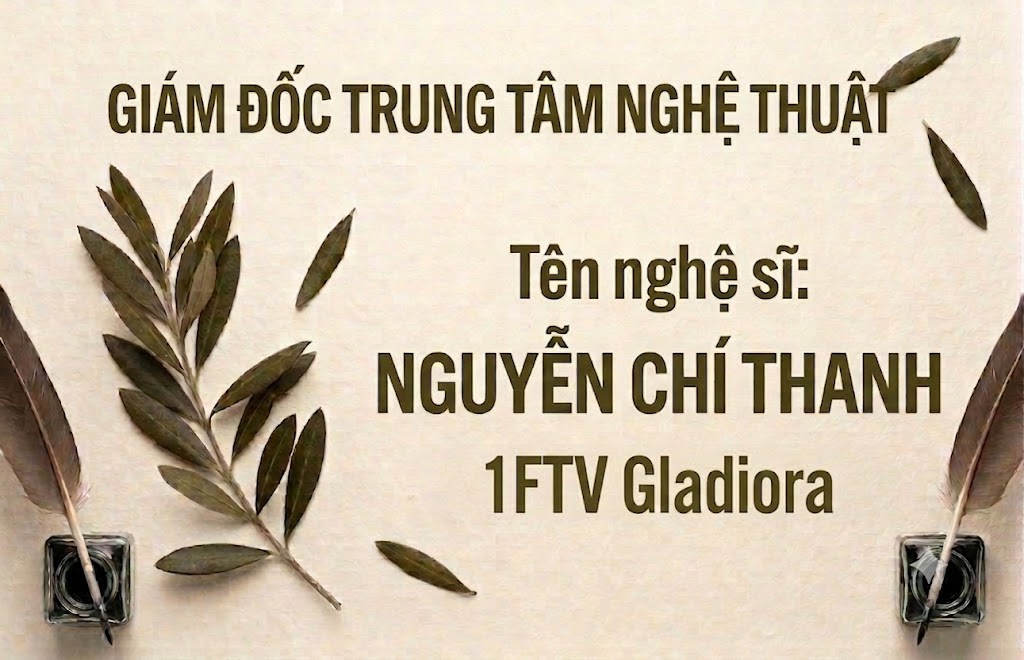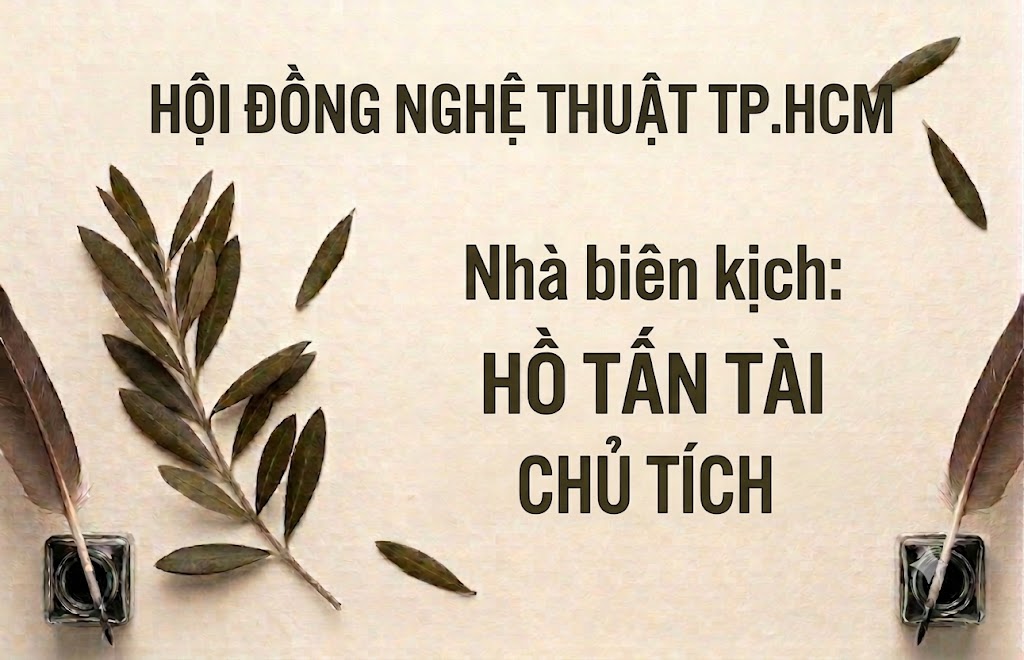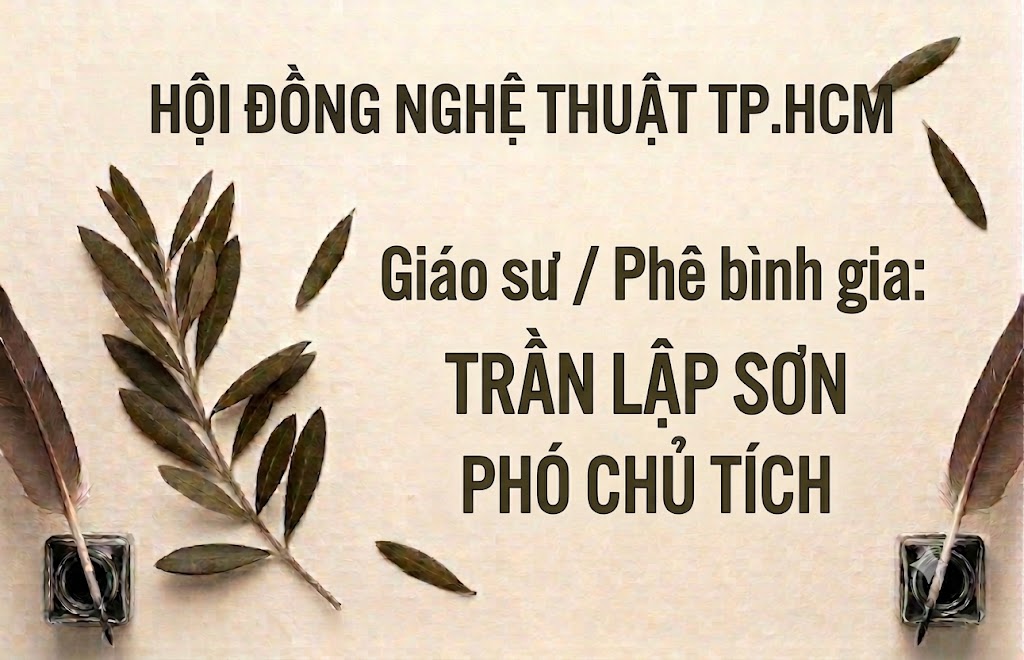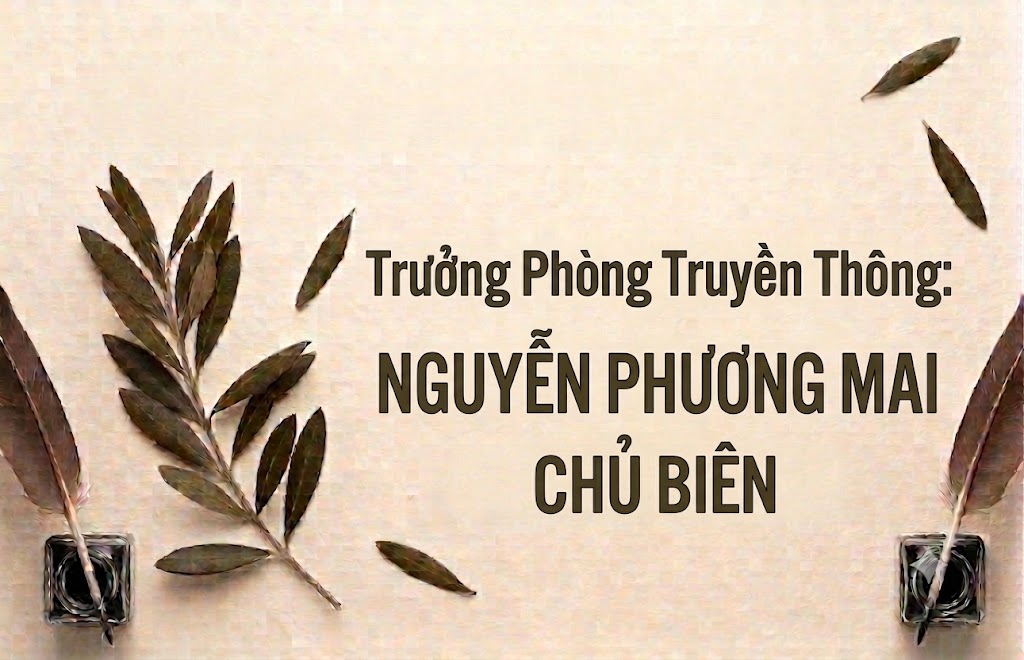
1FTV Gladiora
Trong xu hướng thiết kế tối giản hiện đại, các phông chữ không chân mang cấu trúc hình học tròn trịa luôn là lựa chọn hàng đầu của các designer.
Một kiểu chữ vừa thanh lịch, sạch sẽ lại vừa mang nét trẻ trung sẽ giúp các sản phẩm truyền thông của bạn dễ dàng tiếp cận và thu hút người xem hơn.
Nếu bạn đang tìm kiếm một bộ font nhẹ nhàng nhưng đầy tính nghệ thuật để làm tiêu đề video hay ảnh thu nhỏ, thì font 1FTV Gladiora chính là giải pháp lý tưởng.
Giới thiệu về font 1FTV Gladiora
Font 1FTV Gladiora là một bộ chữ thuộc thể loại display không chân mang phong cách geometric tối giản, thanh lịch và vô cùng hiện đại.
Bộ phông chữ này được tối ưu hóa hoàn chỉnh ở phiên bản 1.000, mang lại cấu trúc đường nét vô cùng mượt mà và nhất quán cho từng ký tự.
Sản phẩm xuất hiện trong bài viết sở hữu định dạng opentype layout cao cấp, đi kèm chứng thực kỹ thuật số và hệ thống nét chuẩn truetype outlines.
Nhờ các thông số kĩ thuật tối ưu này, phông chữ có khả năng hiển thị vô cùng sắc nét trên mọi nền tảng thiết kế đồ họa hiện đại mà không lo bị lỗi vỡ hình.
Đặc điểm nổi bật của phong cách thiết kế Gladiora
Sức hút lớn nhất của font 1FTV Gladiora đến từ phom dáng tròn trịa mang đậm tính chất hình học kết hợp cùng nét chữ thanh mảnh.
Các ký tự như o, e, c, a được tạo hình với những đường cong hoàn hảo, gợi lên sự thân thiện, nhẹ nhàng và đầy tinh tế cho toàn bộ văn bản.
Điểm cộng rất lớn của bộ font này là việc hỗ trợ trọn vẹn cả hệ thống chữ thường bên cạnh bộ chữ viết hoa cơ bản.
Điều này giúp bạn dễ dàng phối hợp hoa thường linh hoạt, khiến dòng tiêu đề trở nên tự nhiên, cuốn hút và thoáng mắt hơn khi hiển thị.
Khoảng hở giữa các nét chữ được tính toán khoa học, đảm bảo phần nội dung văn bản luôn rõ ràng và cực kỳ dễ đọc trên mọi thiết bị di động.
Để phông chữ vận hành mượt mà trên hệ thống máy tính, phiên bản font 1FTV Gladiora đã trải qua quy trình xử lý thông số kĩ thuật kỹ lưỡng.
Hệ thống khoảng cách chữ và độ giãn dòng đã được căn chỉnh chuẩn xác, giúp các từ khi đứng cạnh nhau luôn giữ được khoảng trống thẩm mỹ tốt nhất.
Bên cạnh hệ thống chữ cái hoa và thường đồng bộ, phông chữ còn tích hợp đầy đủ dãy số từ 0-9 cùng hệ thống các ký tự đặc biệt, dấu câu thông dụng (1234567890.:,;'"(!?)+-*/=).
Bản Việt hóa này giúp bạn hoàn toàn yên tâm sáng tạo các nội dung tiếng Việt mà không lo gặp phải tình trạng lỗi hiển thị hay thiếu ký tự khi gõ.
Hình ảnh demo thực tế của font 1FTV Gladiora
Để giúp bạn dễ dàng hình dung khả năng co giãn và hiển thị linh hoạt của phông chữ này trên các kích thước khác nhau, hãy cùng xem qua bảng mô phỏng thực tế:
Kích thước nhỏ (12pt – 24pt): Các nét chữ thanh mảnh và bộ chữ thường vẫn hiển thị rất rõ ràng, ngay ngắn, cực kỳ dễ đọc trên màn hình điện thoại di động.
Kích thước lớn (36pt – 72pt): Đây là không gian lý tưởng để font chữ phô diễn toàn bộ sự thanh lịch, tạo hiệu ứng thị giác hiện đại và cao cấp cho các tiêu đề chính.
Ứng dụng của font Gladiora trong thiết kế đồ họa và làm video
Sở hữu nét cá tính tối giản và cấu trúc hoa – thường linh hoạt, font 1FTV Gladiora mở ra không gian ứng dụng rộng lớn cho các dự án truyền thông:
Thiết kế ảnh thu nhỏ mạng xã hội: Đây là lựa chọn tuyệt vời cho các video thuộc chủ đề vlog đời sống, phong cách sống, chia sẻ kiến thức hoặc thời trang để tăng tính thanh lịch.
Làm tiêu đề và phụ đề cho video ngắn: Kiểu chữ đứng thanh thoát này rất thích hợp để làm phụ đề chạy chữ cho video Tiktok, Reels hay Shorts, giúp người xem dễ dàng theo dõi.
Banner và poster quảng cáo doanh nghiệp: Hoàn hảo cho các poster giới thiệu sản phẩm mỹ phẩm, banner chương trình ưu đãi hoặc các ấn phẩm truyền thông đòi hỏi sự gọn gàng, tinh tế.
Nhận diện thương hiệu phong cách tối giản: Phù hợp làm logo dạng chữ, biểu ngữ hoặc thiết kế nhãn mác cho các thương hiệu thời trang local brand, tiệm cà phê hoặc các studio sáng tạo hiện đại.